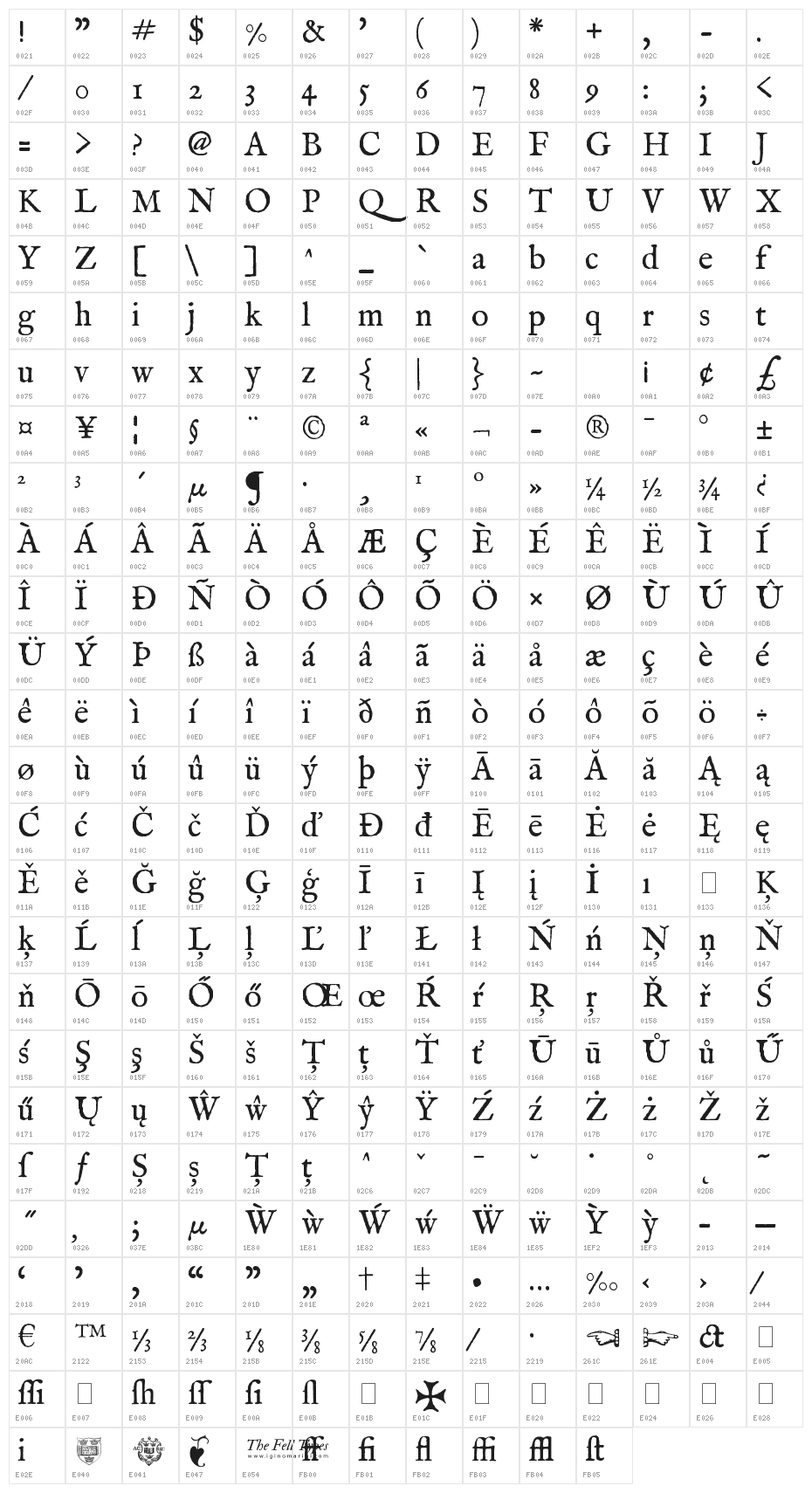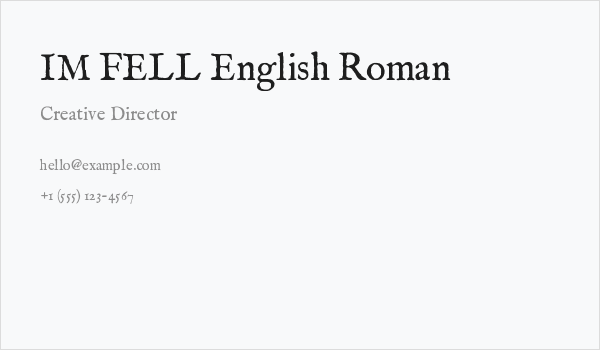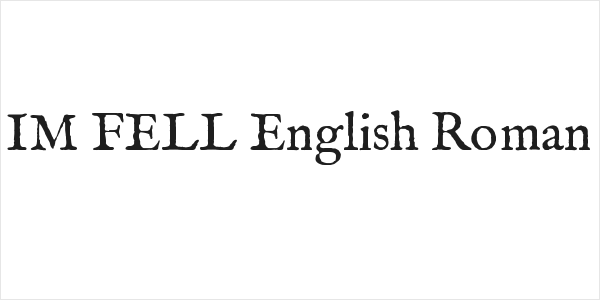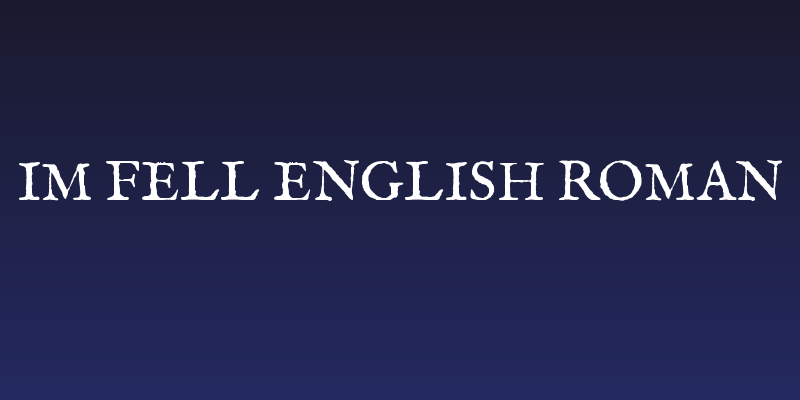
IM FELL English Roman Font
✎ Old fashioned
| Proiecte propuse | Ideal for projects requiring a traditional or historical touch, such as book covers, invitations, or branding for heritage-themed businesses. |